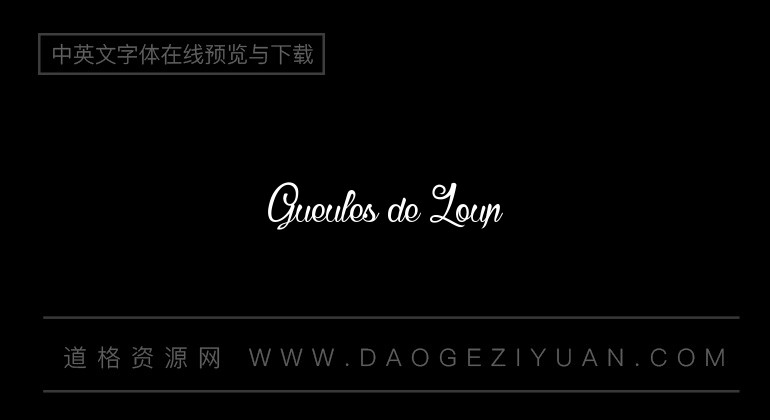
Gueules de Loup是一种非常有特色的手写字体。它的设计灵感来自于草原上的野狼,它的名字在法语中也是“狼嘴”的意思。 Gueules de Loup字体的特点在于它的“手写风格”,每个字母都像是由人手写而成,有着一些自然的、不完美的笔画和线条。同时,它的线条也是比较粗的,有一种粗犷的感觉。 这种字体适合用于一些需要特殊效果的场合,比如海报、广告、包装等。它能够为设计带来一种强烈的个性化和视觉冲击力,但由于它的较为个性化的设计,也不适合应用于一些正式的场合。内容介绍
Gueules de Loup是一款非常不错的手写艺术字体,具有很好的视觉感,适合于文化类的宣传设计、商业类品牌的广告和产品包装设计以及个性化文字排版等较多场景。